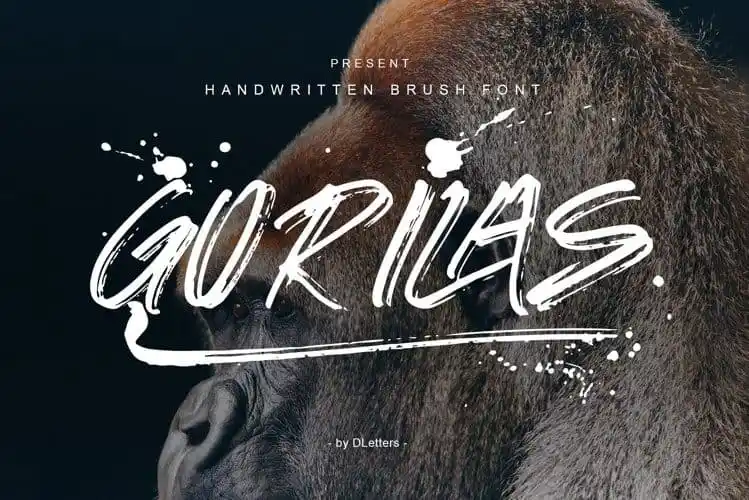
Gorilas Brush Font é uma fonte tipográfica de traço com correntes criada por DLetters Std. Esta fonte traz a essência natural dos traços feitos à mão, com suportes completos para letras maiúsculas e caracteres numéricos e pontuação. A presença de ligaduras em Gorilas Brush Font o torna perfeito para projetos ambiciosos que precisem de uma aparência criativa e única. Se você está procurando por uma fonte de traço com um ar despojado, esta é a escolha certa. Com seu estilo de traço disponível, Gorilas Brush Font oferece o suporte necessário para incorporar letras maiúsculas em qualquer projeto. Além disso, o design cuidadoso e a inclusão de ligaduras permitem que você personalize ainda mais as suas criações, criando textos impactantes e personalizados. Para designers gráficos amadores ou profissionais, Gorilas Brush Font é uma ótima fonte para explorar novos estilos. O seu design cuidadoso e a sua natureza natural fazem dele um excelente parceiro quando vem à hora de criar texturas interessantes e expressivas. Não importa qual projeto esteja em andamento, esta fonte tem o poder de deixá-lo impressionado com a facilidade que ele lhe dá para inovar no design gráfico.